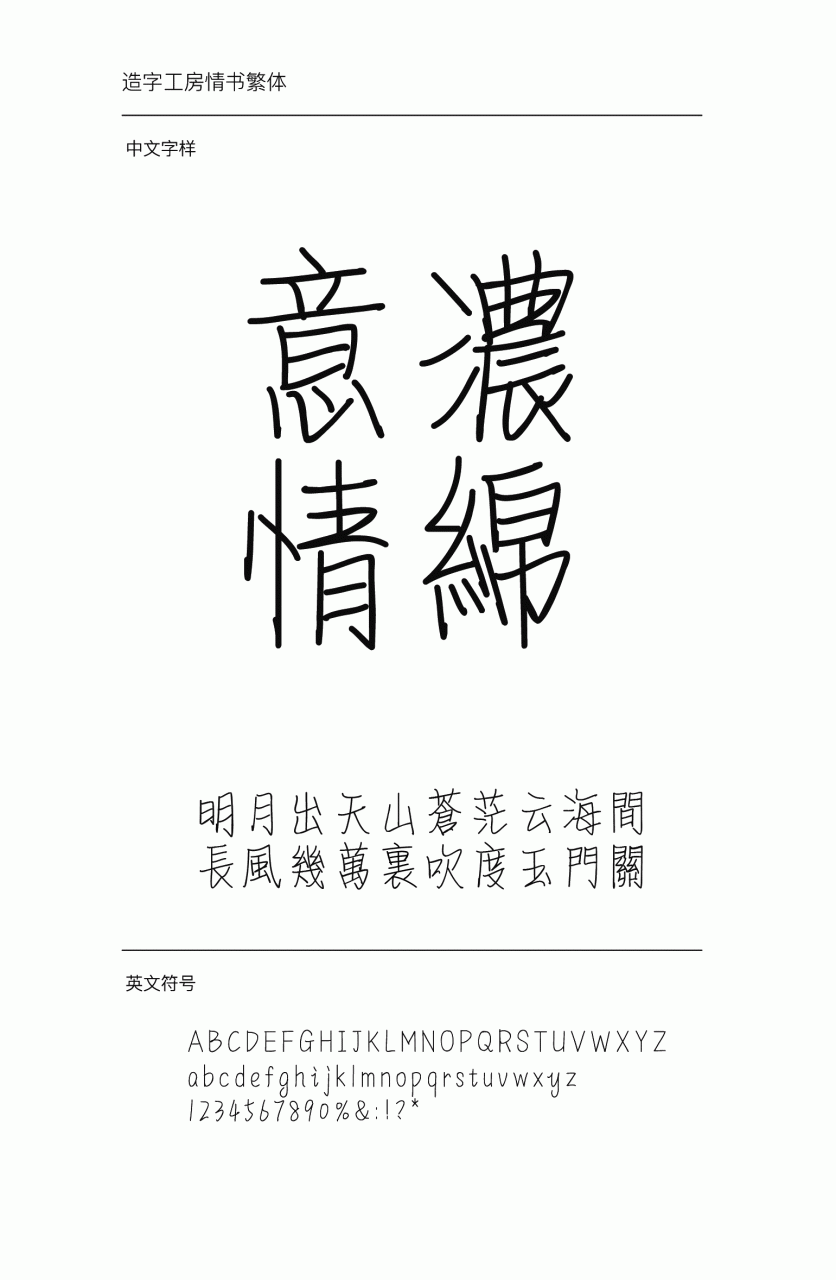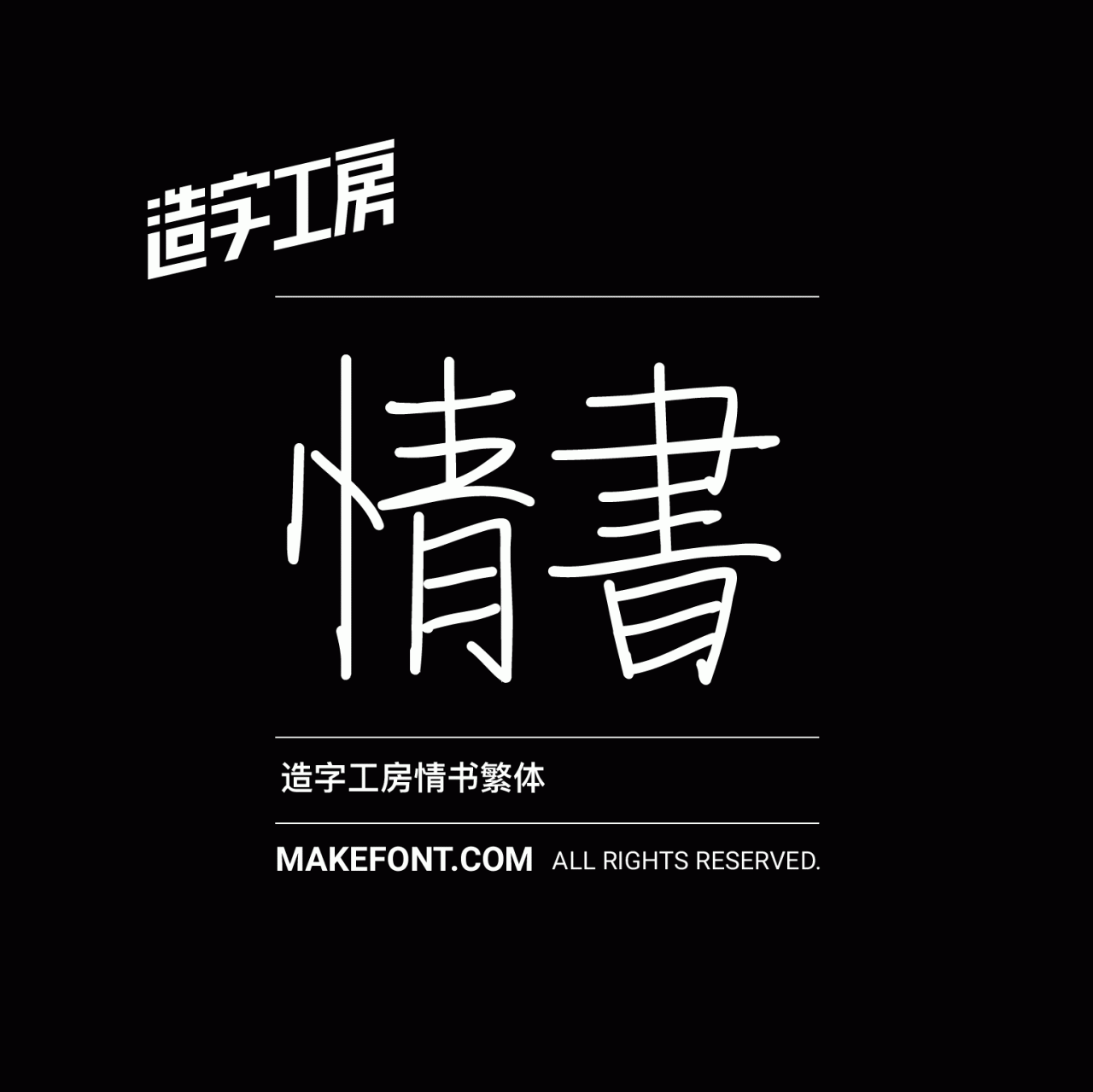
造字工房情书繁体设计说明
造字工房情书繁体由造字工房字体设计师成瑜在情书简体版本基础上完善而成,其字形俊秀、遒劲有力,优雅中透出知性的气息。文从字顺,字形笔画柔美俊秀、刚柔并济,结构自然洒脱,充满活力朝气的青春气息,完美呈现了手写汉字之美,具有很强的自由应用性。适用于广告、信函或正文用字。 本字体为繁体字库,采用OpenType/CID 格式,Adobe-GB1-5编码。